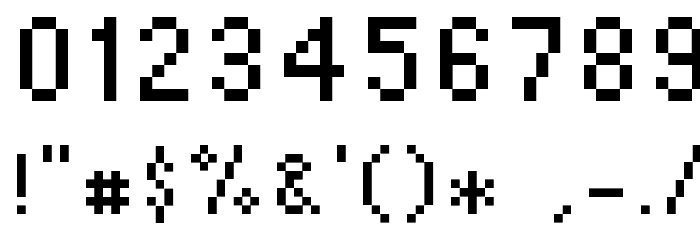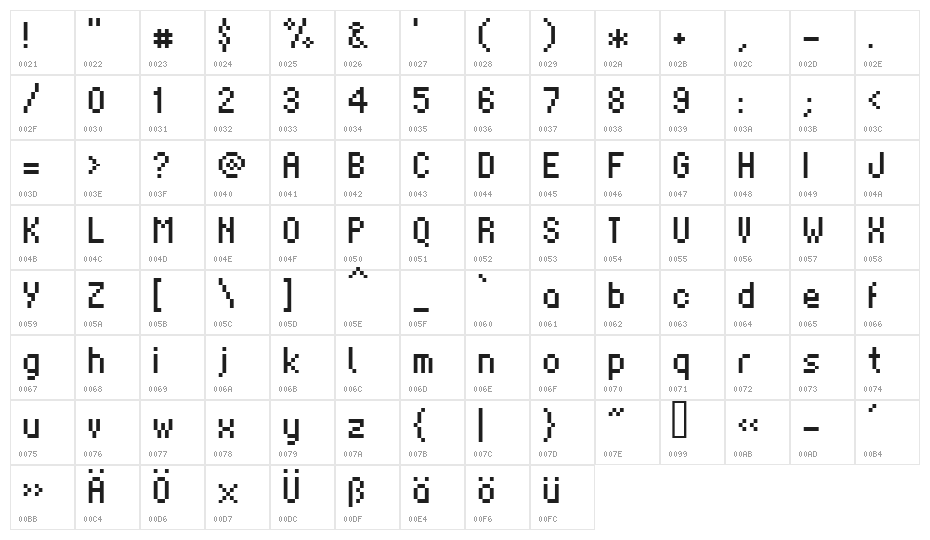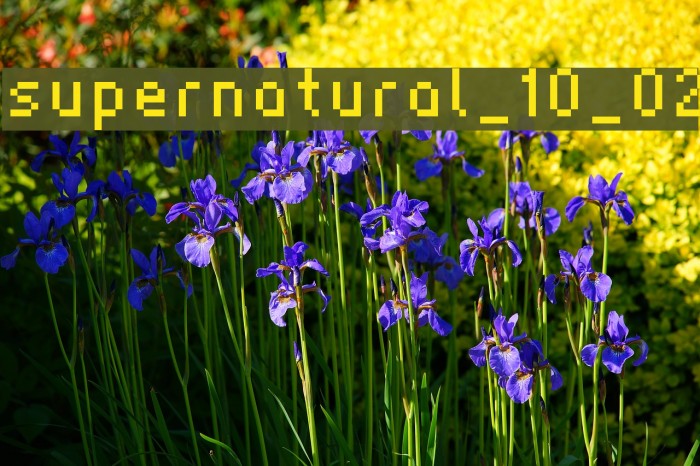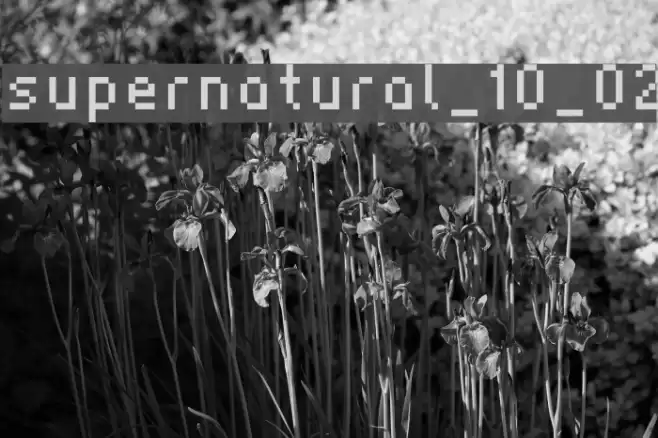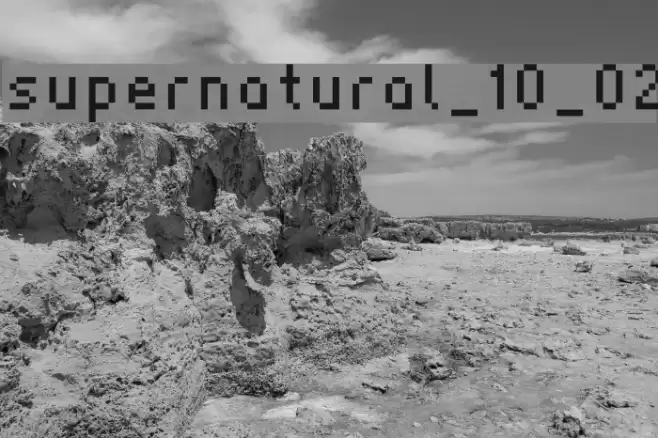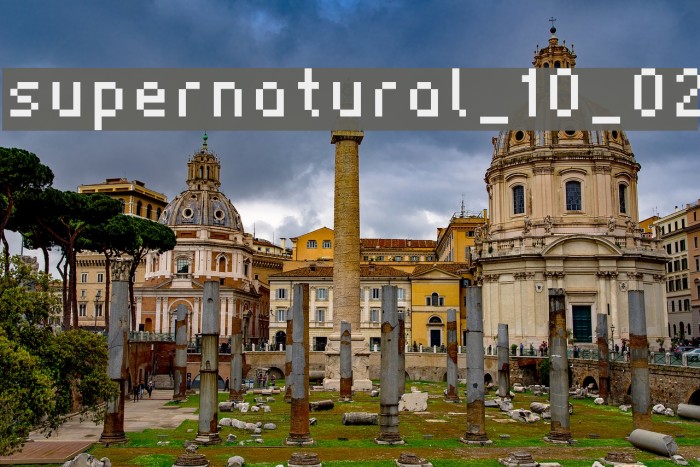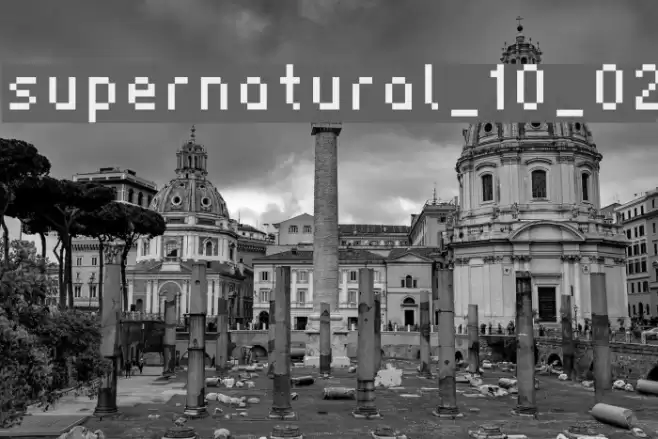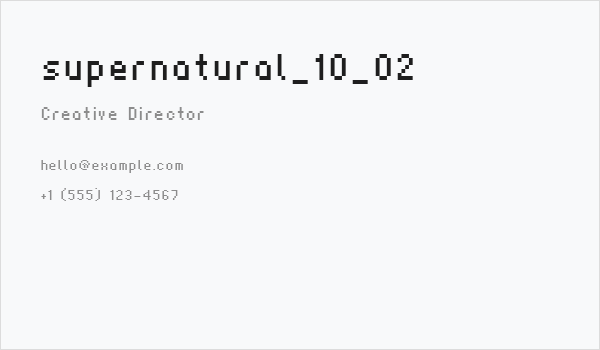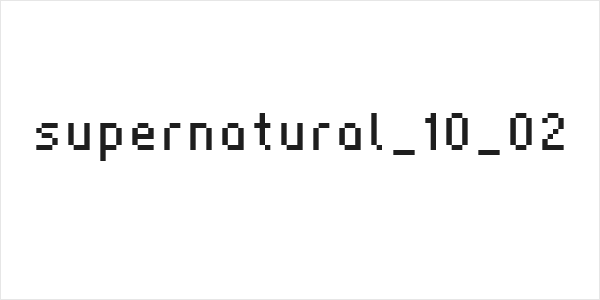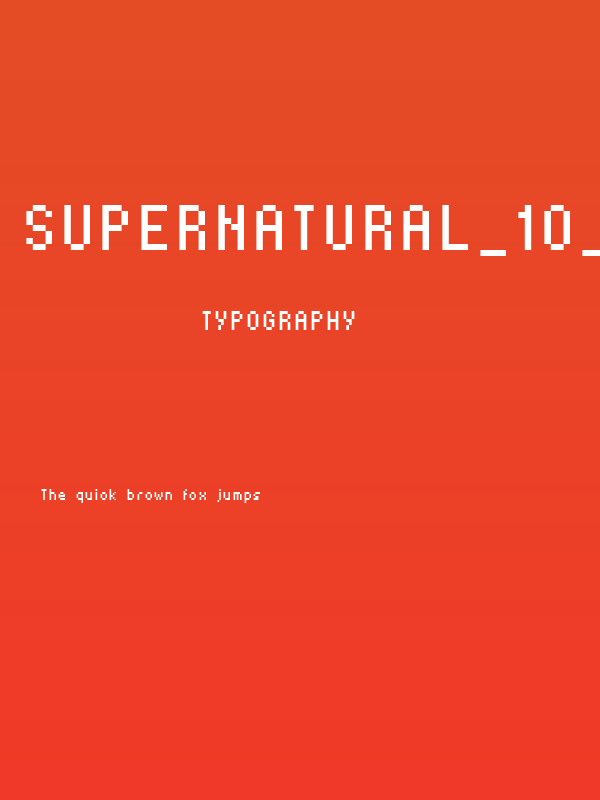
supernatural_10_02 Font
Font by Sven Stuber - www.superlooper.de
| Gesamtstil | Vintage |
| Anwendungsfall | Logos, Headlines, Digital Art |
| Vorgeschlagene Projekte | Ideal for retro video game graphics, tech-themed designs, digital art projects, and any creative work that seeks to evoke a sense of nostalgia for early computing. |